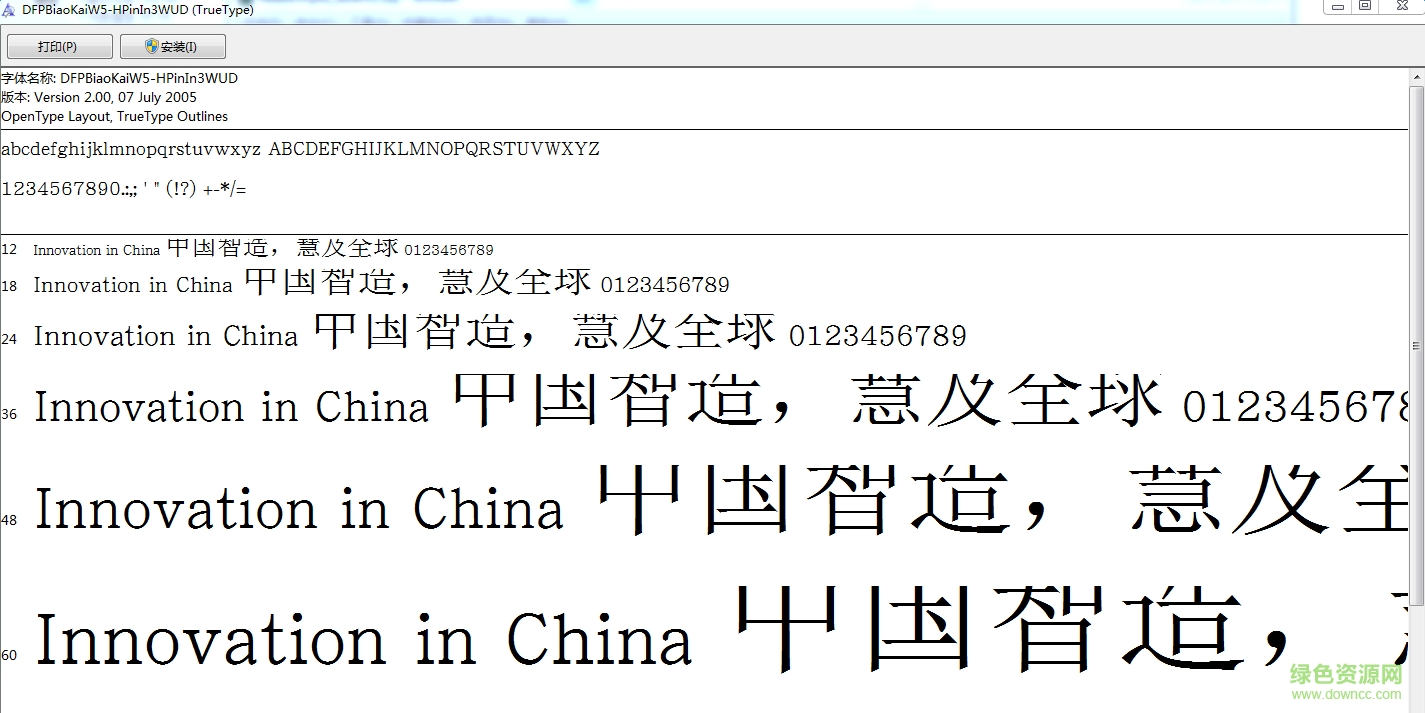
華康標(biāo)楷W5漢音下U字體是一款華康類w5標(biāo)楷體字體軟件,標(biāo)楷的字體給人非常正規(guī)的感覺(jué),深受廣大年輕人的喜愛,還有更多好看字體盡情期待,歡迎到綠色資源網(wǎng)下載體驗(yàn)!
華康標(biāo)楷W5漢音下U是一款華康類w5標(biāo)楷體字體,字體效果比較正規(guī),喜歡黑體字的朋友可以下載使用看看效果如何。